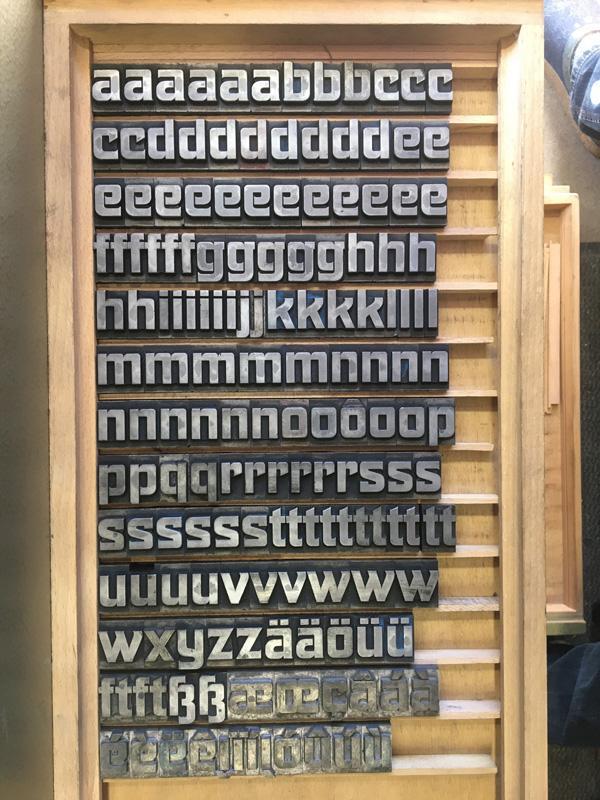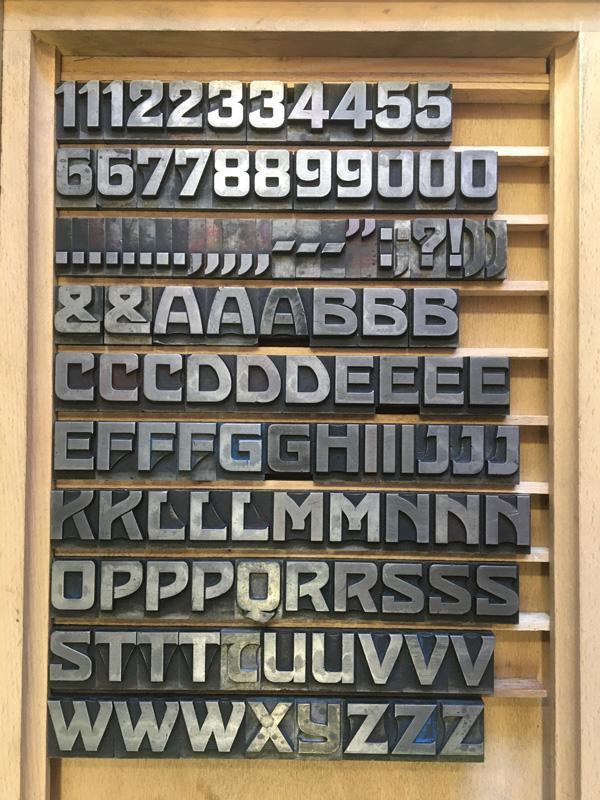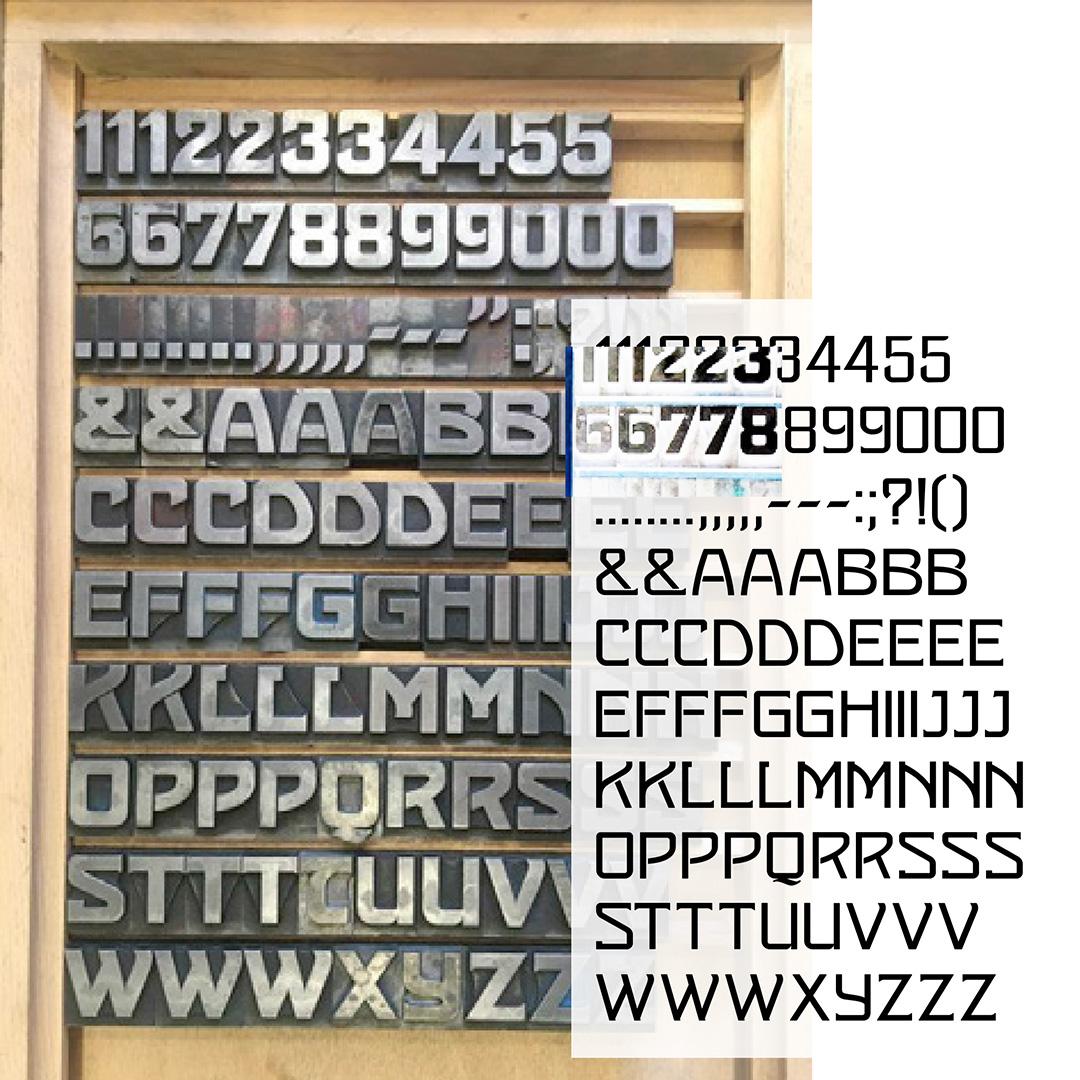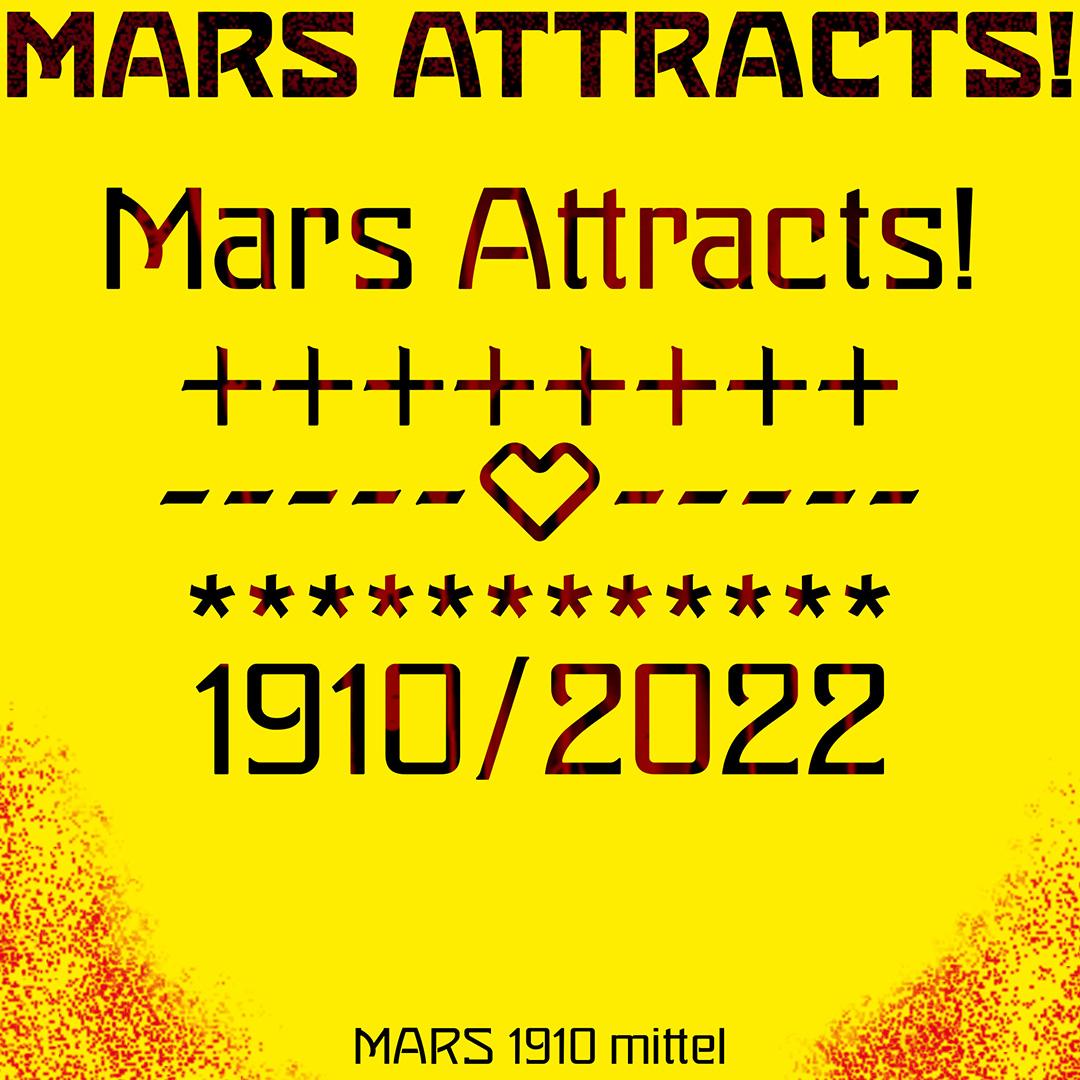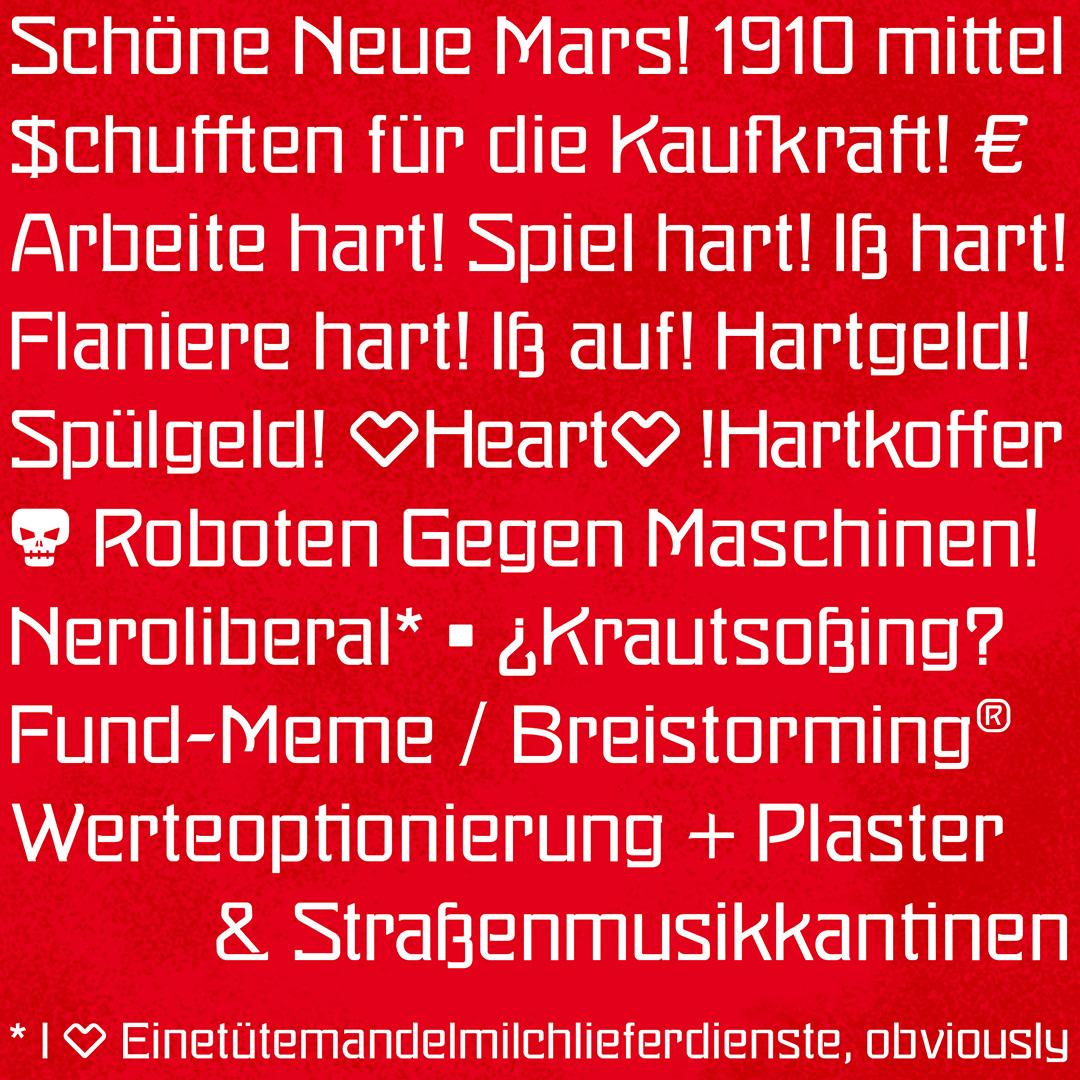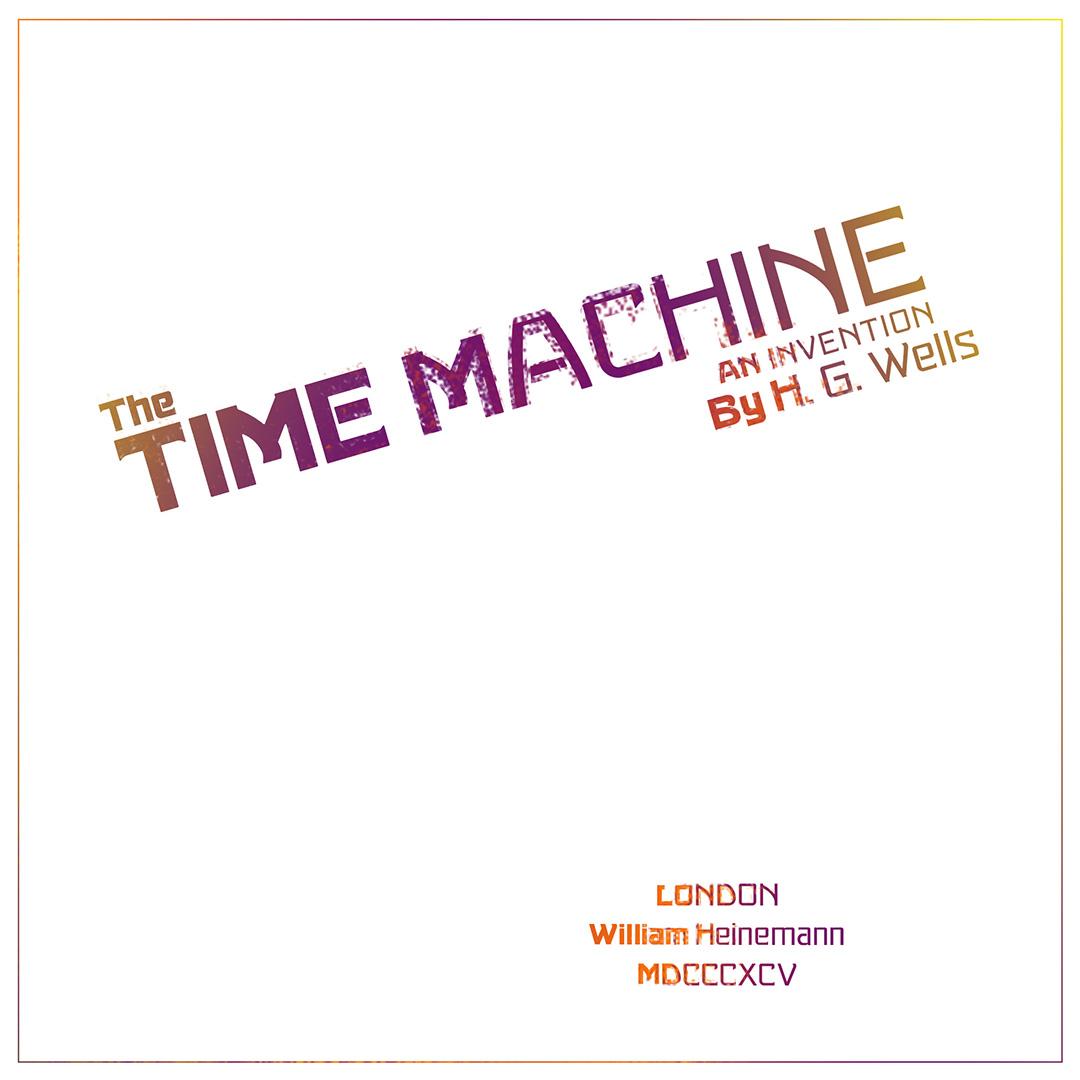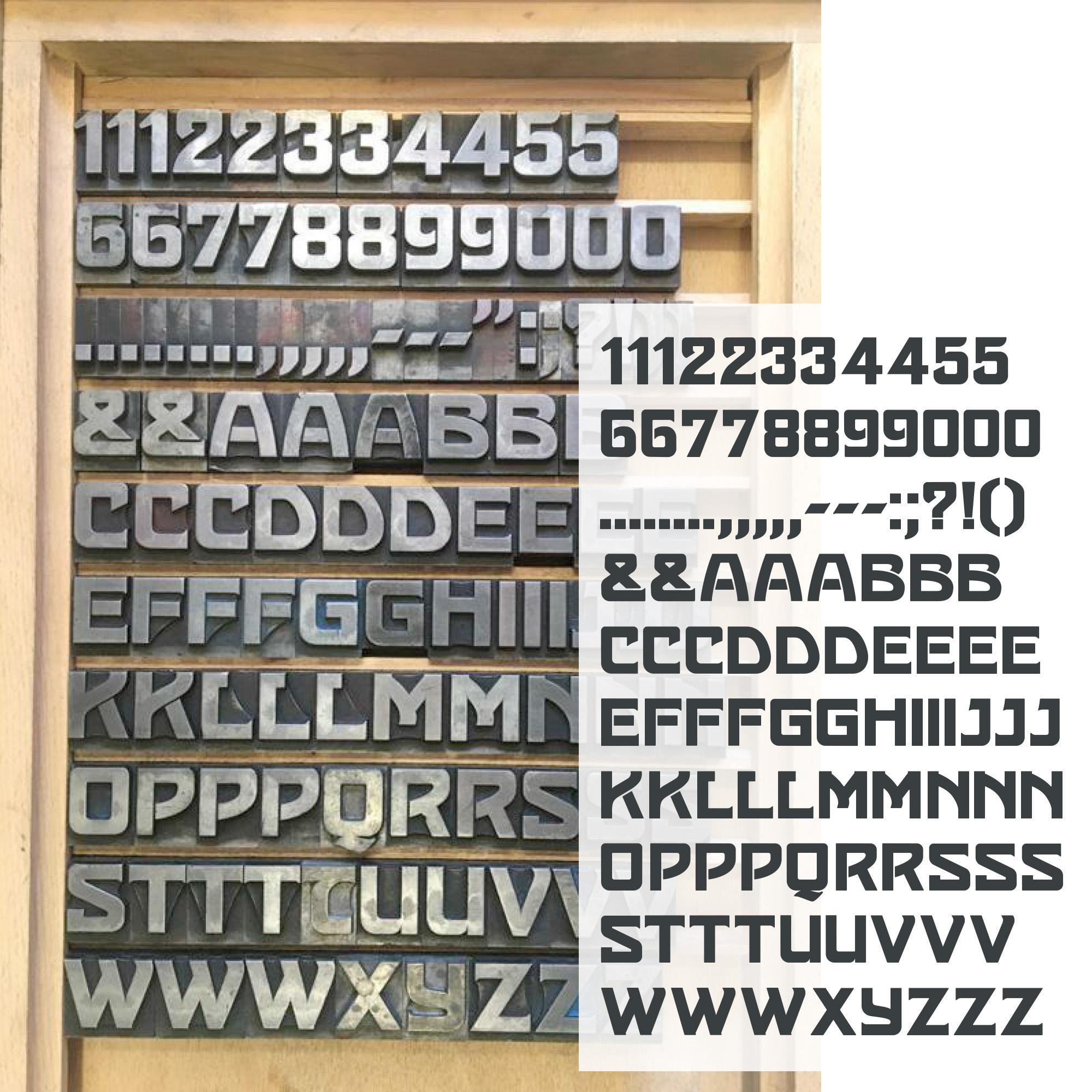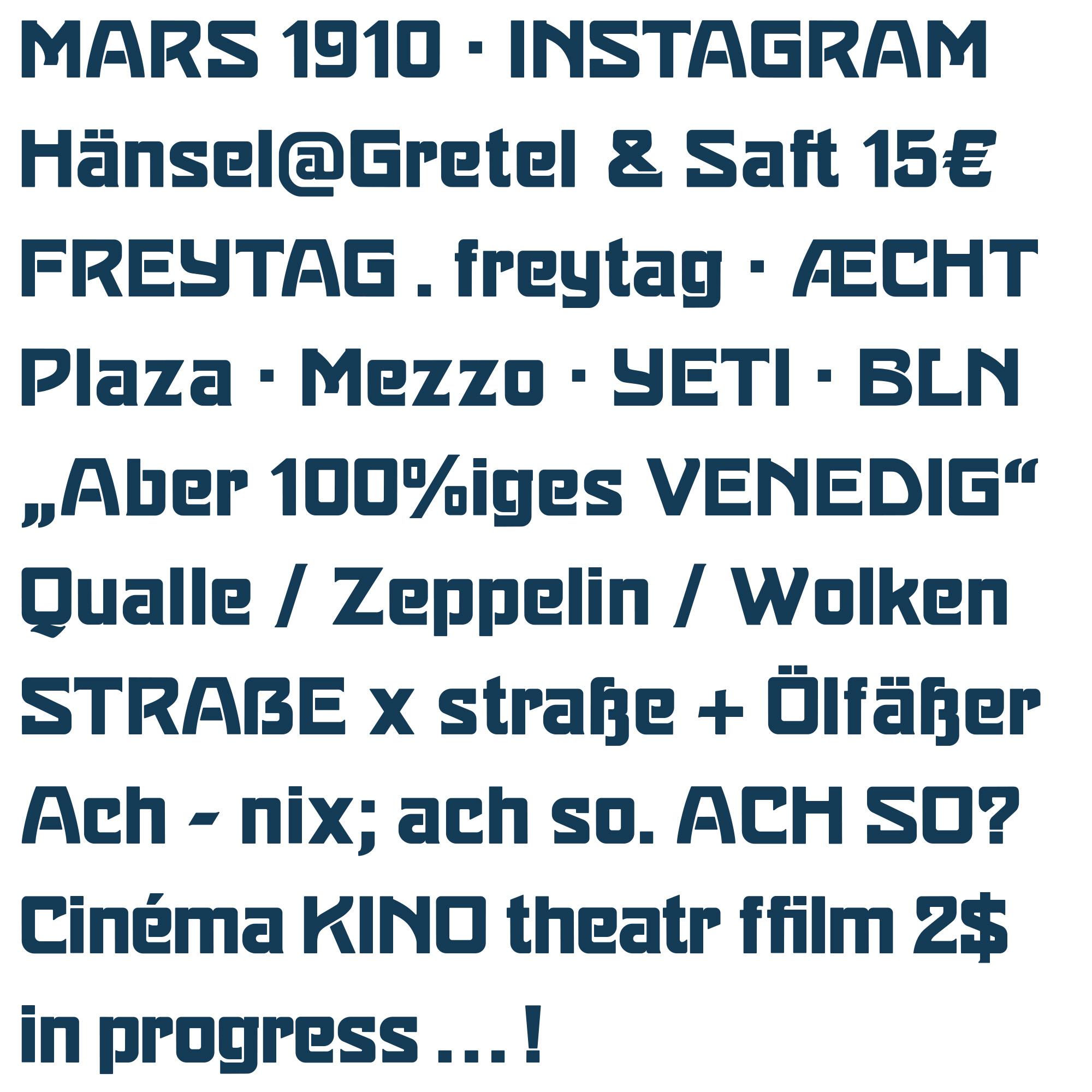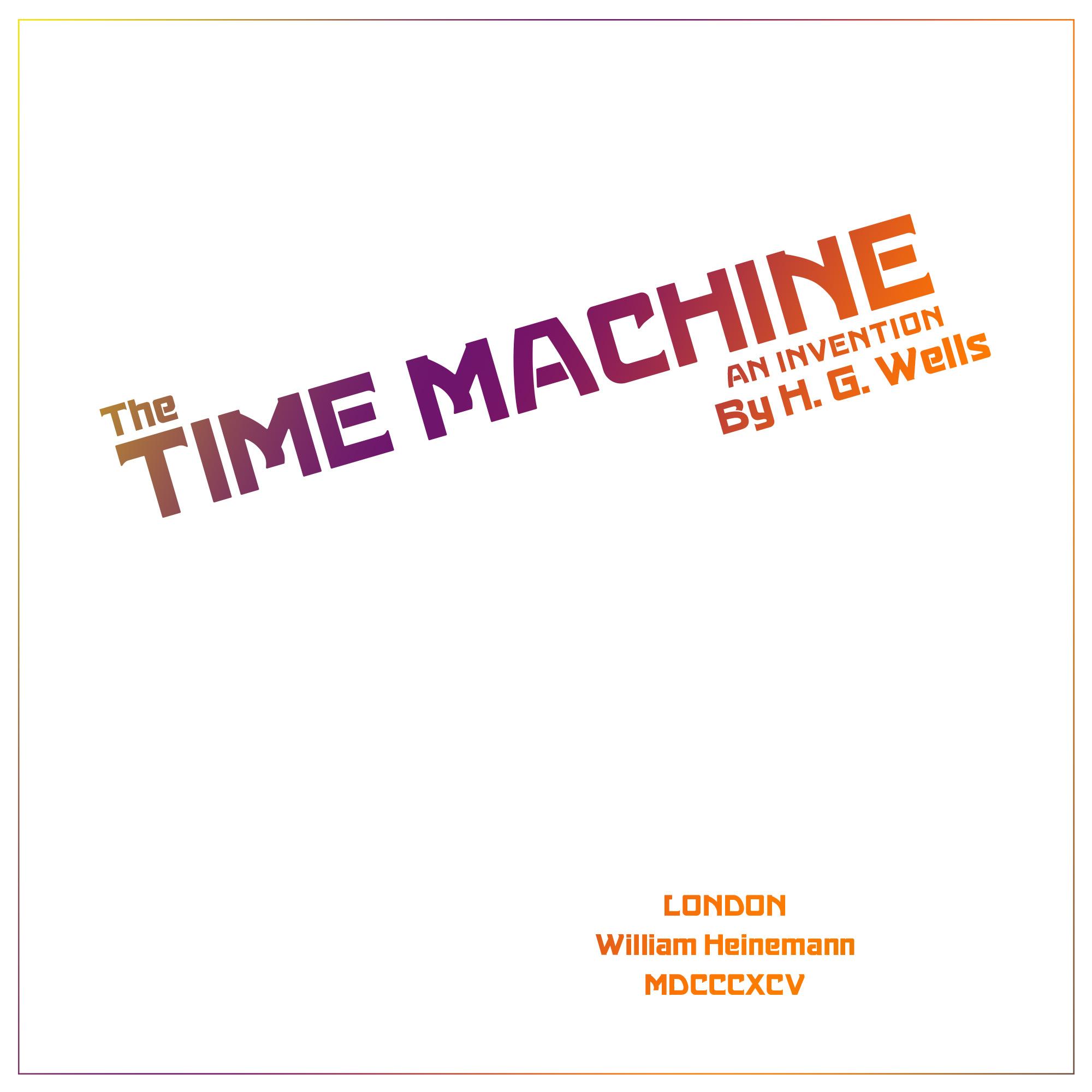
Identifikation unbekannte Bleischrift
wieder einmal hat eine Bleischrift in Plakatgröße 6 Cicero (27 mm Kegel) ihren Weg zu uns gefunden. Der Guß erfolgte auf Hohlkegel um Material und Gewicht einzusparen. Es gibt keine Gußmarke und der Gußkanal-Abschluß ist der einer professionellen Massengießmaschine. Dies bedeutet, daß die Schrift nicht als "Kleinauflage" gegossen wurde, sondern als normale Schrift zur Verfügung stand.
Das Schriftbild selbst erinnert einen ein bißchen an Jugendstilschriften, sieht andererseits aber auch technisch aus. Die Frage wäre nun ob jemand diese Schrift erkennt und bei der Identifikation helfen kann.
Eine schöne Schrift, wie ich spontan finde. Gibt es die digital? Sucht man mit dem „alten“ Namen?
Naja, die finde ich im Vergleich wenig überzeugend. :-? Aber wer weiß - vielleicht kommt noch die Mars Grotesk irgendwann…
Als ich die Fotos hier fand probierte ich grade mit Glyphs Mini herum und konnte nicht widerstehen.